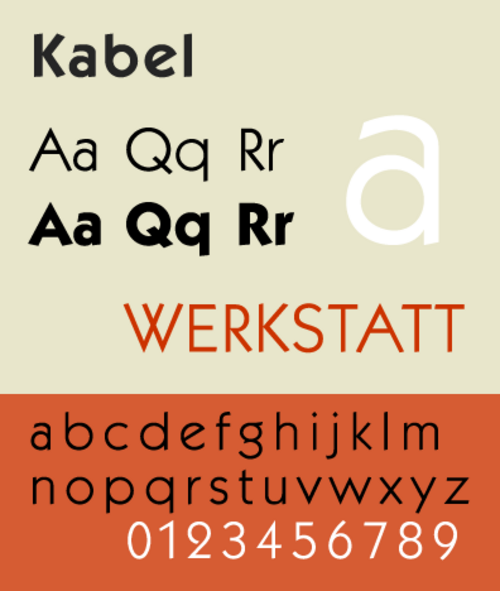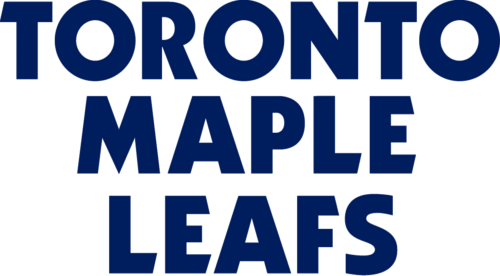
كابل (نوع الخط)
Kabel هو خط هندسي بدون serif صممه رودولف كوخ وأصدرته شركة Klingspor في عام 1927. [ 1 ]
ينتمي خط كابل إلى النمط الهندسي للخطوط غير المزخرفة، الذي كان رائجًا في ألمانيا وقت ابتكاره. يستند الخط بشكل عام إلى بنية الدائرة والخطوط المستقيمة، ولكنه مع ذلك يتبنى عددًا من القرارات التصميمية غير المألوفة، مثل ارتفاع حرف x المنخفض بدقة (مع أنه أكبر في الخط العريض)، وحرف e المائل، ونهايات الحروف ذات الزوايا غير المنتظمة، لإضفاء رقة وعفوية توحي بفن الخط الأنيق الذي برع فيه كوخ. وقد صدرت منه نسخ معاد إصدارها ونسخ رقمية متعددة.
يُظهر خط كابل تأثراً بالتعبيرية بقدر تأثره بالحداثة، ويمكن اعتباره خطاً أحادي الخط بدون زوائد، مُشابهاً لخط كوخ-أنتيكا من تصميم كوخ ، إذ يتشارك معه في العديد من أشكال الحروف ونسبها. ويتجلى ذلك في انخفاض ارتفاع حرف "x" وحرف "g" ذي الطابقين مع حلقة سفلية كبيرة مفتوحة جزئياً، على غرار خط تروي من تصميم ويليام موريس ، وحرف "e" ذي الخط المركزي المائل، على غرار خطوط عصر النهضة المبكرة، وهو ما يُلاحظ أيضاً في تصاميم موريس للخطوط. تُقطع نهايات الخطوط الرأسية والأفقية بزاوية، غالباً ما تكون قائمة على اتجاه الخط، مما يوحي بالكتابة بالقلم. وهذا ما يُعطي خط كابل انطباعاً بأنه لا يستقر تماماً على خط الأساس، مما يُضفي عليه حيويةً ونشاطاً أكبر من خط فوتورا. وتختلف الأحرف الكبيرة اختلافاً كبيراً في العرض، وتُظهر تأثراً بالأحرف الرومانية المربعة ، كما في حرف "M" العريض وحرف "E" الضيق. أما حرف "W" الكبير، فيتخذ شكلاً رباعي الأطراف. في النسخة العادية، يمتد ساق حرف "U" الكبير إلى اليمين، وهو ما يبرز بشكل خاص في النسخة الخفيفة. أما حرف "Y" الكبير فيشكل خطاً متصلاً بذيله.
سوّق كوخ خط كابل بعرض نموذج يُظهر الأحرف الكبيرة التي يُفترض أنها مُستمدة من شبكة بناء من مستطيلات ودوائر مثالية، لكن والتر تريسي وآخرين لاحظوا أن هذا الرسم لا يُشبه في الواقع حروف الطباعة، التي رُسمت بوضوح بحرية تامة بدلاً من استخدام هندسة غير مُصححة: "ربما رسم كوخ حروفه دون قيود، ثم قام بـ"ترشيدها" لاحقًا... من الواضح أن كوخ لم يكن رجلاً يتقيد بقواعد تعسفية. في كابل لايت، يبلغ طول أذرع الحرف E ثلاثة أطوال مختلفة، وقاعدة الحرف R أعمق من قاعدة الحرف B، وفي الحرف P أعمق من ذلك... ولا يحتوي الحرف Y على الساق الرأسية الموضحة في الرسم التخطيطي. باختصار، يتحكم إحساس كوخ بالأسلوب، بدلاً من أي صيغة هندسية. والنتيجة هي أبجدية من الأحرف الكبيرة التي ترتبط ببعضها البعض بشكل مثالي دون الحاجة إلى "تناغم رياضي"... إنها، في رأيي، أجمل الأحرف الكبيرة من نوع sans-serif على الإطلاق." [ 2 ]
فيما يتعلق بالاسم، تشير ملاحظات إصدار Adobe لنسختها من Kabel إلى ما يلي: "لم يُسمَّى Kabel نسبةً إلى أي كابل محدد ، على الرغم من اكتمال تلفريك تسوغسبيتزي في عام 1926، وافتتاح خط تلغراف فاكس بين برلين وفيينا في عام 1927. كان للاسم مكانة تقنية في ذلك الوقت ( يُعرف جيدًا كتالوج كابلات NKF لبيت زوارت لعام 1927)، وهو في الأساس اسم مجازي وإيحائي، تورية تشير إلى كل من البنية أحادية الخط للخط، ودور الطباعة كوسيلة للتواصل." [ 3 ]
صدرت النسخة الأصلية من قلم كابل بأربعة أوزان: خفيف (صدر أولاً)، متوسط/كتابي، ثقيل، وأسود. يتميز الأخير بتصميم مُعاد ابتكاره ليناسب الخطوط السميكة، مع ارتفاع أكبر لحرف x وانتظام أكثر، دون النهايات المائلة للأوزان الأخف. [ 2 ] كما صدرت أيضًا نسخة بتصميم خطي، "بريزما"، ووزن رئيسي "زيبيلين"، وأوزان مضغوطة. [ 4 ]
قدمت بعض إصدارات الحروف المعدنية بدائل أسلوبية ، أي حروفًا بديلة بتصميم مختلف. وقد قلل العديد منها من غرابة خط كابل، وجعله على وجه الخصوص أقرب إلى خط فوتورا ، الذي كان سائدًا جدًا في الطباعة في تلك الفترة. [ 2 ] [ 1 ] (كان هذا العرض للبدائل الشبيهة بفوتورا، مثل حرف "a" ذي الطابق الواحد، والذي أطلق عليه المؤرخ بول شو اسم "استئصال فوتورا"، شائعًا بين خطوط sans-serif الأخرى في ذلك الوقت، بما في ذلك خط جيل سانس من مونوتيب ، وخط مترو من لينوتايب، وخط إربار . [ 5 ] )
أُصدر تصميم كابل في الأصل من قِبل شركة Gebr. Klingspor Foundry، واستمرت شركة Stempel Foundry (التي اشترت Klingspor عام 1956، بعد أن كانت تمتلك بالفعل بعض الأسهم) في توفيره لفترة وجيزة لأنظمة الطباعة الضوئية . [ 1 ] ولا تزال شركة Linotype تبيع كابل بصيغة رقمية. [ 6 ] ونظرًا لشعبية كابل، باعت شركات أخرى، مثل شركة Alphabet Innovations التابعة لفيل مارتن، العديد من التعديلات والنسخ المقلدة البسيطة. [ 1 ] [ 7 ] [ 8 ] [ 9 ] [ 10 ] وقد حدث هذا بشكل خاص خلال فترتي الطباعة الضوئية والطباعة الرقمية، مستغلةً غياب الحماية الدولية لحقوق التأليف والنشر للخطوط. [ 1 ]
كابل ITC
تم تصميم نسخة فيكتور كاروسو لعام 1975 للطباعة الضوئية لصالح شركة الخطوط الدولية (ITC) ، بعد ترخيص حقوق التصميم من شركة ستيمبل. وتتبع هذه النسخة نهج ITC القياسي المتمثل في زيادة ارتفاع حرف x بشكل ملحوظ ، مصحوبًا بمجموعة موحدة من الأوزان من Book إلى Ultra، مع الحفاظ على شكل النهاية المائلة في الأوزان العريضة على سبيل المثال. [ 1 ]
باعت شركة ITC أيضًا قلم ITC Grizzly، وهو نسخة معدلة من القلم ذي الوزن الثقيل. [ 11 ]
كابل جديد
إصدار عام 2016 من مارك شوتز، يتميز بفارق ارتفاع بين النسخة الأصلية والنسخة الرقمية بتقنية ITC، ويتوفر بتسعة أوزان مختلفة مع أنماط مائلة مكملة لها. ومن السمات المميزة الأخرى لـ "Neue Kabel" البدائل الأسلوبية مثل الأحرف الصغيرة "a" و"g" و"e" و"l"، والعناوين الدائرية والمربعة بزاوية 45 درجة. [ 1 ] [ 12 ] [ 13 ]
ابتكر الراهب بيكو بيسالا برنامج كابالا، وهو برنامج مفتوح المصدر لإحياء فن الخط، وقد سُمّي على اسم كلمة من لغة بالي تعني "لقمة طعام" نظرًا لاستخدامه المقصود في المنشورات الدينية البوذية. [ 14 ] هذا الإصدار مستوحى من مجموعة أوزان وبنية ITC، ولكنه يضيف عددًا من الميزات بما في ذلك الخط المائل والأحرف الصغيرة والأحرف المركبة.
استند تصميم راي لارابي "كندا 1500" بشكل فضفاض على تصميم كابل الأصلي، مع ارتفاعات حروفه الصغيرة المنخفضة. بعد تكليفه بتصميم مجموعة كاملة من الأحرف لدعم لغات كندا ، تبرع لارابي بالنسخة الأصلية، "كندا 150"، لحكومة كندا عند اكتمالها في عام 2015 لاستخدامها في احتفالات كندا بالذكرى المئوية والنصف لتأسيسها ، ثم أطلقها في الملكية العامة قبل يوم كندا 2017 (يوم الذكرى المئوية والنصف) كهدية عيد ميلاد لبلده الأم.
قام مصمم الخطوط الفنلندي، تومي هابارانتا، بتصميم خط Kaapeli الذي استوحاه من خط Kabel. [ 15 ]
- يُستخدم كابل في لعبة مونوبولي الشهيرة . [ 16 ]
- تم استخدام كابل ITC Kabel Demi في لعبة Sonic Boom: Rise of Lyric .